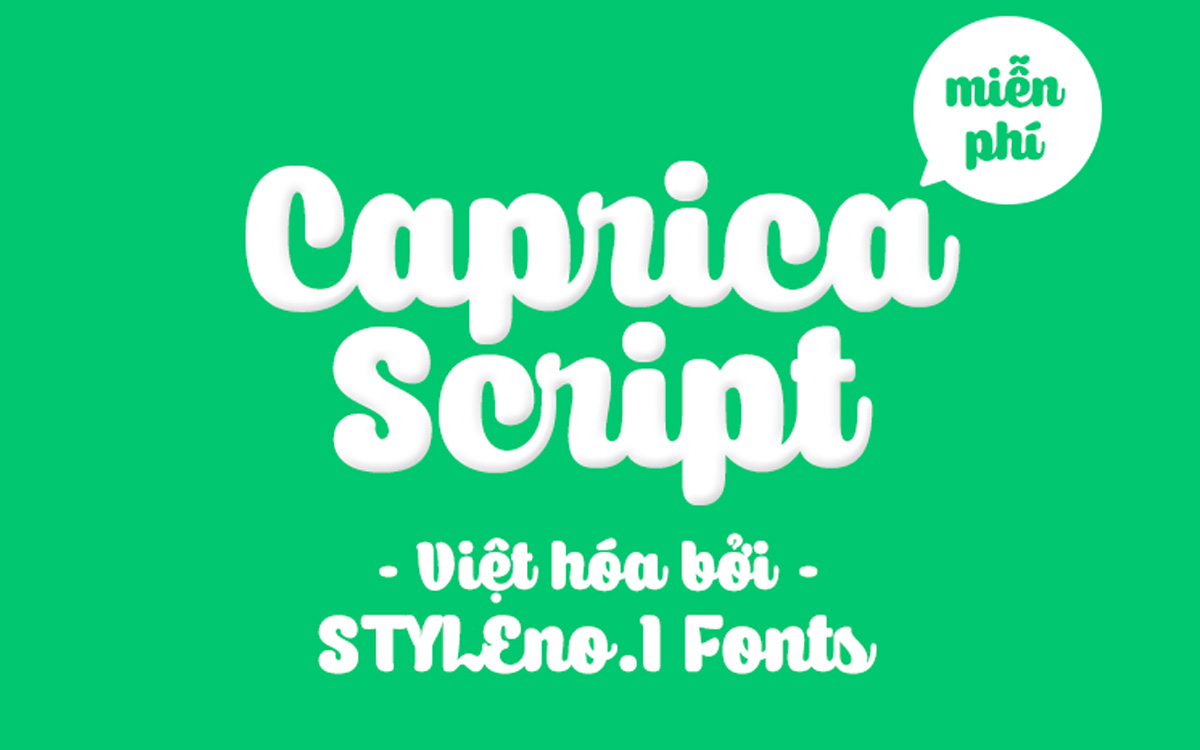
Trong ngành thiết kế đồ họa F&B (Food & Beverage), việc lựa chọn một phông chữ thể hiện được trọn vẹn “hương vị” và “tính cách” của thương hiệu là yếu tố cốt lõi tạo nên sự thành công. Font chữ đồ ăn mềm mại SVN-Caprica Script chính là giải pháp nghệ thuật hoàn hảo, mang đến vẻ đẹp ngọt ngào, tinh tế và vô cùng quyến rũ cho mọi ấn phẩm truyền thông ẩm thực. Với các đường nét uốn lượn tự nhiên như dòng sốt kem hay kem tươi mịn màng, bộ phông chữ này nhanh chóng chiếm trọn cảm tình của giới thiết kế chuyên nghiệp.
Font Chữ Đồ Ăn Mềm Mại SVN-Caprica Script – Giải Pháp Thiết Kế Ẩm Thực Độc Đáo Và Quyến Rũ
Hình ảnh nhận diện thương hiệu ẩm thực không chỉ đòi hỏi sự bắt mắt về màu sắc mà còn phụ thuộc rất lớn vào ngôn ngữ typography. Một thực đơn được trình bày chỉn chu, một chiếc bao bì bánh ngọt xinh xắn hay một banner quảng cáo món ăn cuốn hút đều cần sự góp mặt của những nét chữ mang tính khơi gợi xúc giác. Phông chữ SVN-Caprica Script được sinh ra để đáp ứng hoàn hảo tiêu chí đó. Được việt hóa tỉ mỉ bởi đội ngũ SVN, font chữ này loại bỏ hoàn toàn rào cản lỗi font tiếng Việt, giúp các designer dễ dàng sáng tạo nên những tác phẩm đồ họa mang đậm dấu ấn riêng.
Sự kết hợp giữa phong cách Script cổ điển và hơi thở hiện đại giúp SVN-Caprica Script trở thành công cụ đắc lực cho các nhà hàng, quán cà phê, tiệm bánh và các thương hiệu thực phẩm cao cấp. Dưới đây là những tính năng vượt trội khiến bộ phông chữ này trở thành sự lựa chọn hàng đầu trong lĩnh vực thiết kế ẩm thực.
1. Nét chữ mềm mại, uốn lượn tự nhiên tôn vinh thẩm mỹ ẩm thực
Điểm đặc trưng nhất của SVN-Caprica Script nằm ở cấu trúc nét chữ vô cùng uyển chuyển. Các đường nhấp nhô, uốn lượn được gọt dũa khéo léo, tạo cảm giác mềm mại giống như dòng sô-cô-la đun chảy, lớp kem tươi nhung mịn hay những sợi mì pasta thơm ngon. Sự nhịp nhàng trong từng nét bút không chỉ tạo nên nhịp điệu thị giác êm ái mà còn tác động mạnh mẽ đến tâm lý người xem, khơi gợi cảm giác thèm ăn và sự ngon miệng ngay từ ánh nhìn đầu tiên.
Bên cạnh đó, font chữ sở hữu độ dày nét (weight) được tính toán hợp lý, không quá mảnh làm mất nét khi in ấn, cũng không quá dầy gây cảm giác thô kệch. Điều này giúp các tiêu đề chính (headline) trên poster, menu luôn nổi bật và giữ được sự sang trọng vốn có.
2. Tối ưu hóa Việt hóa chuẩn xác, hỗ trợ trọn vẹn ký tự tiếng Việt
Một trong những thách thức lớn nhất khi sử dụng các phông chữ script quốc tế là lỗi dấu tiếng Việt (như dấu thanh, các chữ cái ă, ê, ơ, ư…). SVN-Caprica Script đã giải quyết triệt để vấn đề này nhờ bản Việt hóa chỉn chu. Hệ thống dấu câu được thiết kế lại theo chuẩn tỉ lệ vàng, đảm bảo sự hài hòa về mặt thị giác mà không làm mất đi phom dáng gốc của font.</p>
- Khoảng cách dấu tối ưu: Các dấu sắc, huyền, hỏi, ngã, nặng được đặt ở vị trí cân đối, không đè lên nét uốn của chữ cái adjacent.
- Giữ nguyên thẩm mỹ: Đường nét của các ký tự đặc trưng tiếng Việt được vẽ mượt mà, đồng bộ hoàn toàn với phong cách chung của bộ font.
- Tránh lỗi hiển thị: Khắc phục hoàn toàn tình trạng nhảy font hoặc đứt nét khi gõ các từ tiếng Việt phức tạp trong thiết kế thực đơn như “Bánh mì”, “Phở bò”, “Trà sữa”, “Cà phê”.
3. Bộ tính năng OpenType phong phú với Ligatures và Alternates đa dạng
Không dừng lại ở các ký tự cơ bản, SVN-Caprica Script cung cấp một kho tàng ký tự thay thế (Stylistic Alternates) và ký tự nối (Ligatures) vô cùng phong phú. Tính năng này cho phép các nhà thiết kế biến tấu linh hoạt, tạo ra những dòng chữ mang tính cá nhân hóa cao giống như được vẽ tay (hand-lettering) riêng biệt cho thương hiệu.
Nhờ hệ thống ký tự mở rộng này, bạn có thể dễ dàng tạo ra những logo ẩm thực độc bản, những câu tagline uốn lượn đầy nghệ thuật trên bao bì sản phẩm mà không lo đụng hàng. Sự biến hóa đa dạng của các đuôi chữ (swashes) giúp khung hình thiết kế trở nên bay bổng, giàu chất nghệ thuật và thu hút sự chú ý của khách hàng mục tiêu.
4. Ứng dụng đa dạng trong nhận diện thương hiệu F&B và Bao bì thực phẩm
Nhờ sự kết hợp hoàn hảo giữa tính thẩm mỹ và khả năng đọc tốt, font chữ đồ ăn mềm mại SVN-Caprica Script được ứng dụng rộng rãi trong nhiều hạng mục thiết kế khác nhau thuộc ngành F&B:
- Thiết kế Menu (Thực đơn): Làm nổi bật tên các món ăn đặc sắc, tên danh mục đồ uống hoặc các chương trình khuyến mãi đặc biệt.
- Thiết kế Logo & Identity: Đắc lực cho các tiệm bánh ngọt (Bakery), quán cà phê phong cách Vintage/Modern, tiệm trà sữa, nhà hàng Âu hoặc các thương hiệu thực phẩm organic.
- In ấn bao bì & Thẻ bài (Packaging & Tags): Mẫu chữ xuất hiện ấn tượng trên ly giấy, hộp bánh, nhãn dán chai nước, tem bảo hành phẩm chất.
- Truyền thông Kỹ thuật số (Social Media): Tạo sự chú ý cho các banner quảng cáo trên Facebook, Instagram, TikTok đối với các chiến dịch ra mắt món mới.
5. Khả năng tương thích cao và tối ưu hóa cho hiển thị đa nền tảng